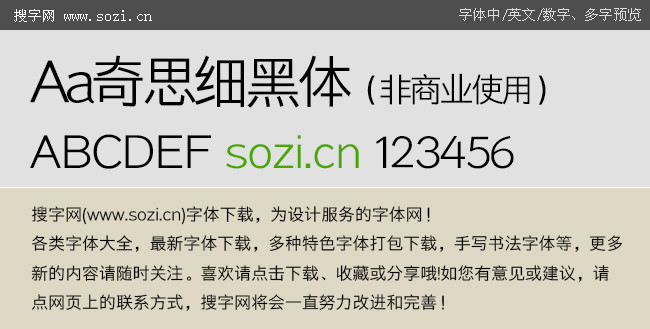
Aa奇思細黑體
搜字網(wǎng)給大家提供一款A(yù)a奇思細黑體(非商業(yè)使用)中文字體下載,該字體是一款簡潔的黑體字體,字體簡潔大方,結(jié)構(gòu)清晰,具有很好的視覺識別性,適用于平面宣傳設(shè)計、網(wǎng)頁設(shè)計、海報設(shè)計等應(yīng)用(此字體為個人非商用版,商用可以聯(lián)系QQ:1006760504)。